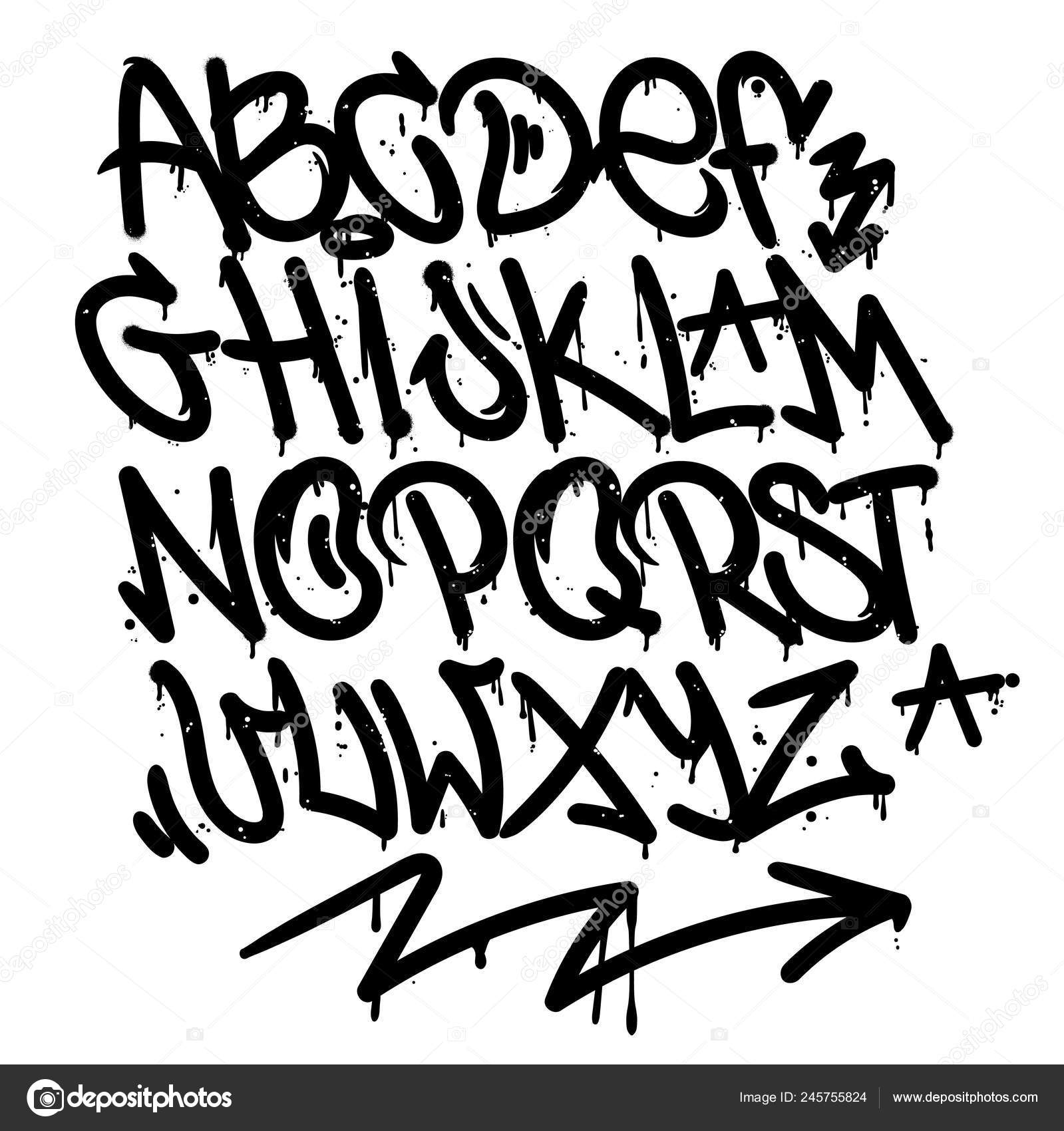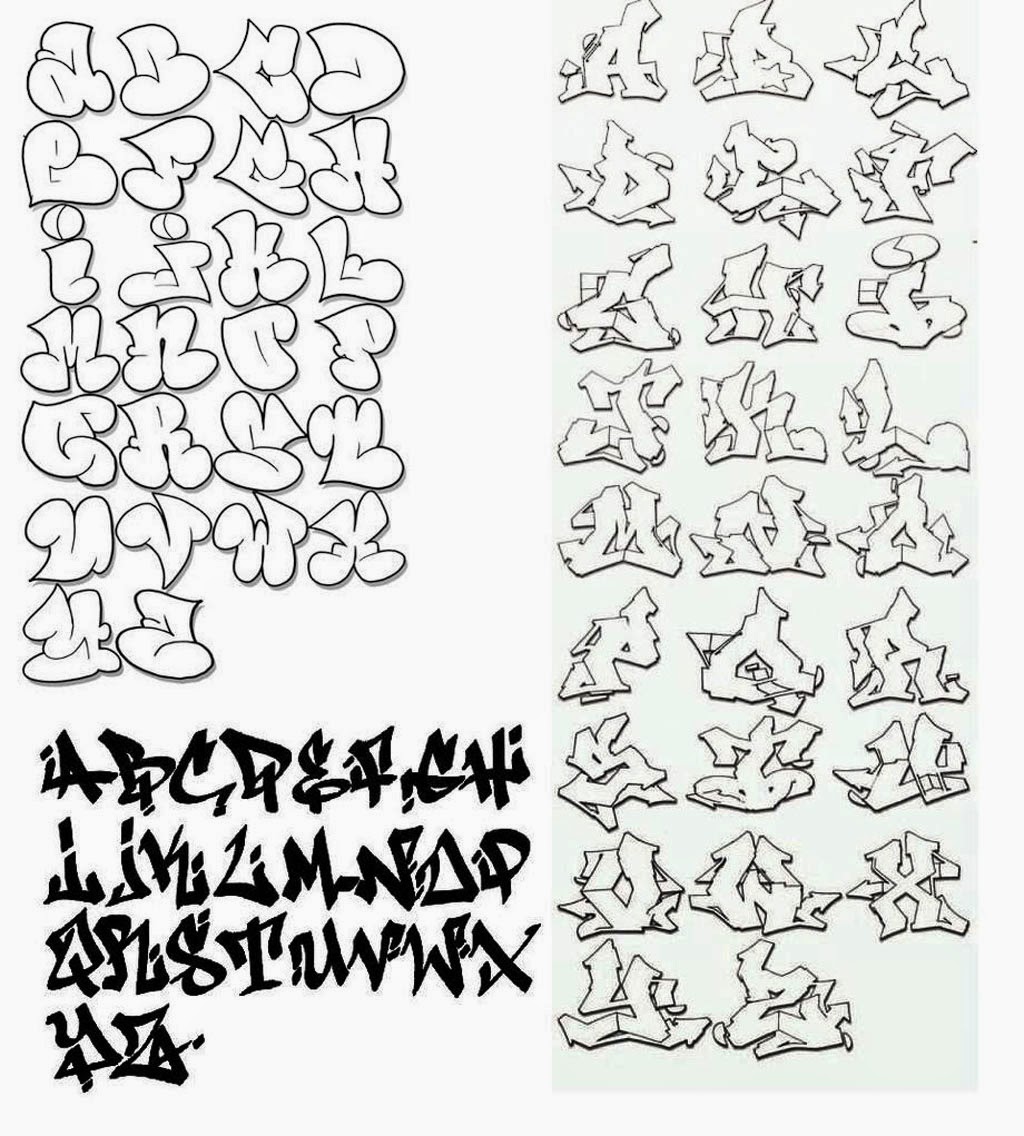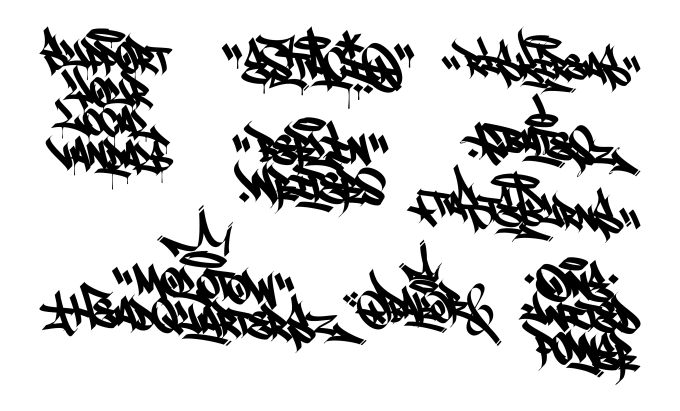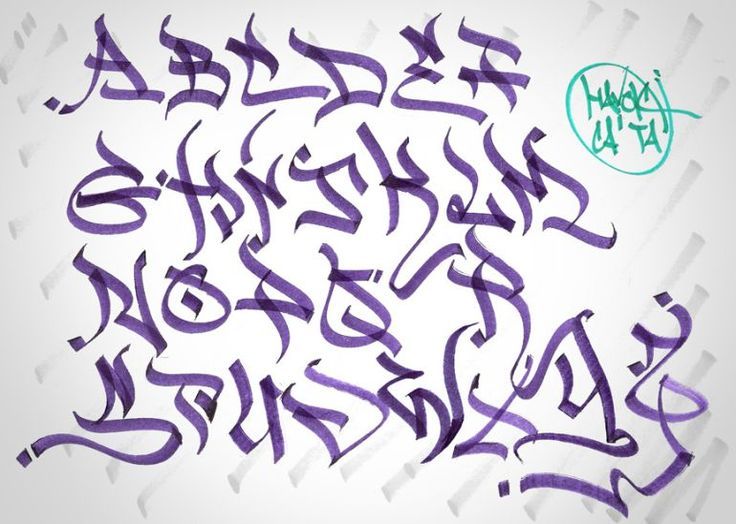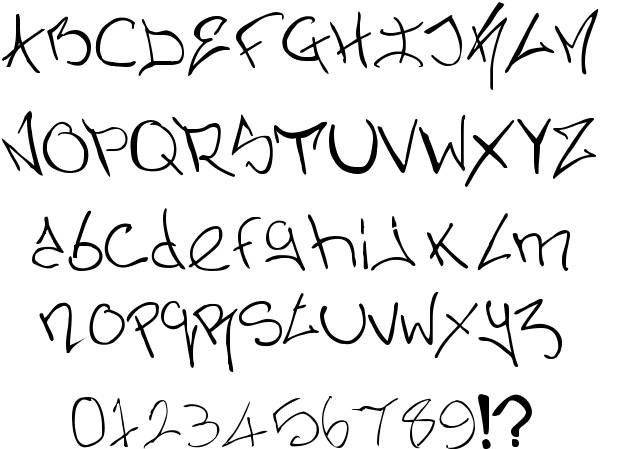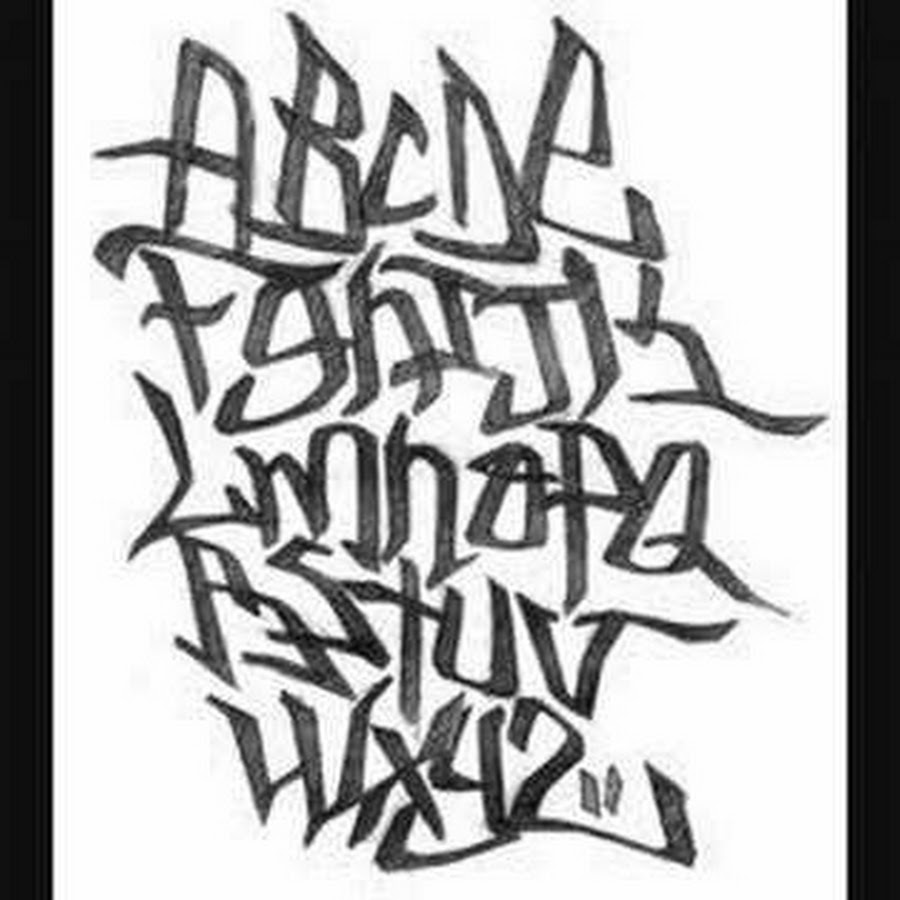
Рисуем теги граффити
Многие современные подростки задумываются над вопросом: как же научиться красиво и правильно рисовать граффити? В данной статье мы рассмотрим все нюансы и секреты рисования. Если внимательно приглядеться, то можно увидеть на стенах заброшенных домов, заборах и гаражах, лестницах и на асфальте яркие и очень интересные надписи, рисунки. Не все люди смогут понять, что это такое изображено. Дело в том, что такое направление называется граффити. Самое интересное то, что это считается искусством. Чтобы нарисовать загадочный рисунок, потребуется много сил и знаний, все не так просто. Данный стиль особенно распространен у подростков и молодых людей. Некоторые личности считают свои рисунки способом самовыражения, а другие думают, что это только порча стен, заборов, домов и других строений.
Если перевести слово «граффити» с итальянского языка, то оно будет значить «нацарапанность». Это специальные надписи, которые обычно наносят на ровные поверхности маркерами, краской либо выцарапывают при помощи острых предметов.
Граффити — это уличное изображение, которое можно увидеть в любом городе. Если вспомнить, что древние люди пытались рисовать на скалах и в пещерах, то даже их рисунки можно легко отнести к современному стилю «граффити».
Откуда появились граффити
А возникли они очень интересно. Это началась с самых древнейших надписей, наскальных рисунков. Благодаря им можно признаться в любви, обратиться к кому-то, раскритиковать кого-то, общаться. Это замечательное искусство зародилось еще со смутных времен, войн, битв и сражений. Однако настоящее современное подобное рисование зародилось в 1970-х годах и разошлось очень быстро по всему миру. Теги граффити распространились благодаря одному молодому человеку из Нью-Йорка, который подрабатывал обычным курьером. Он каждый день ездил в метро, оставляя рисунок тега, который назывался «Таки-183». Через некоторое время об этом молодом человеке были написаны интересные факты в газетах. Благодаря этому удивительному курьеру в настоящее время используются граффити как надписи, логотипы, автографы, картины.
Распространение
С тех времен подростки стали постепенно распространять граффити, оставляя свои рисунки на зданиях, метро, поездах и даже электричках, автобусах, стенах, мостах. В настоящее время такое распространение привело к мобильному уличному стилю. Как придумать тег для граффити? Об этом задумывались даже самые известные творческие личности. В основном, разработкой новых тегов занимались интересные и загадочные художники, которые хотели бы отличаться от обычного общества своей уникальностью, загадочностью и смелостью.
Конечно, не все люди стали поддерживать райтеров за их новое искусство. В некоторых городах, если люди замечали рисующих художников, вызывали полицейских, которые штрафовали их и даже сажали в тюрьму. Из-за этого многие писатели бросали свое дело, пугаясь быть пойманным.
С тех самых 70-х годов стали развиваться новые направления на улицах городов. Каждый художник пытался выразить именно собственную точку зрения в споре, проблеме, выражая мастерство в подобных рисунках.
Создавались разные теги граффити, изображения, рисунки, письма. Стилей огромное множество, поэтому любой рейтер выбирает для себя единственный, помогающих с точностью подчеркнуть саму суть художника.
Борьба с художниками
Когда появился новый стиль, бороться с райтерами стало просто невыносимо, поэтому власти некоторых городов придумали интересное решение: для таких художников выделялись специальные здания и дома, которые можно было бы разрисовывать. К сожалению, таких стен было очень мало, поэтому жаждущим самовыразиться приходилось выходить за рамки допустимого.
Теги граффити и рисунки стали одной частью, которые набирают свою популярность по всему земному шару. В настоящее время очень популярно рисовать в стиле хип-хоп-музыки. Хип-хоповцы научили райтеров многим выражениям и фразам, сленгам и чувству стиля.
Теги граффити для новичков
Если вы любите рисовать и часто наблюдаете за работами других мастеров, то давайте вместе учиться мастерски это делать.
Украсим свой город яркими надписями и рисунками, распространим это замечательное искусство по всему земному шару! Начинаем работу с легкого задания — рисования при помощи ручки или карандаша на бумаге.
Существует большое количество разных стилей, поэтому прежде чем начинать свои художества, необходимо ознакомиться, какими бывают теги для граффити. Список их разновидностей, как вы увидите, довольно внушителен. Выберете себе один вариант, который вам больше понравится. Теперь попытайтесь срисовать с картинки и раскрасить изображение яркими карандашами или фломастерами (можно приобрести текстовыделитель). Самое главное, чтобы все выглядело красиво и неизбито. Для оригинальности добавьте украшения — звездочки, геометрические фигуры, знаки. Прорабатывайте рисунки до тех пор, пока сразу не станет получаться красиво. Только после этого можно изображать теги граффити в общественных местах. В специальных магазинах можно приобрести краски, фломастеры (для новичков) и другие привлекательные вещи.
Рисуем граффити
Многие думают, что научиться рисовать очень просто, но на самом деле это трудный, сложный и долгий процесс, который требует внимательности и знаний, терпеливости и внутренней собранности. Многие известные райтеры делали первые шаги при помощи срисовывания тегов с картинок. Если вы хотите оригинальности, то постарайтесь самостоятельно поработать над созданием своего собственного стиля.
Когда вы приступаете к рисованию граффити краской, то сначала сделайте только очертания рисунка или письма. Линии проводите плавно, аккуратно и быстро, так как краска может потечь и все испортить. Самый простой рисунок выполняется с применением только одной краски, а сложный — от двух или трех. Смешиванием цветов увлекаются настоящие профессиональные художники, которые отлично разбираются в рисовании на улице.
Не размещайте их слишком близко друг к другу, оставляя достаточно места для дальнейших исправлений и дополнений. Попробуйте придать своему рисунку стандартный вид граффити. Когда вы ознакомитесь с этой частью рисунка, попробуйте сделать изображение объемным.
Добавьте тени и блики. Меняйте давление на карандаш, это позволит вам создавать линии разной толщины. Такого же эффекта можно добиться, используя несколько типов простых карандашей — заостренные и слегка тупые.